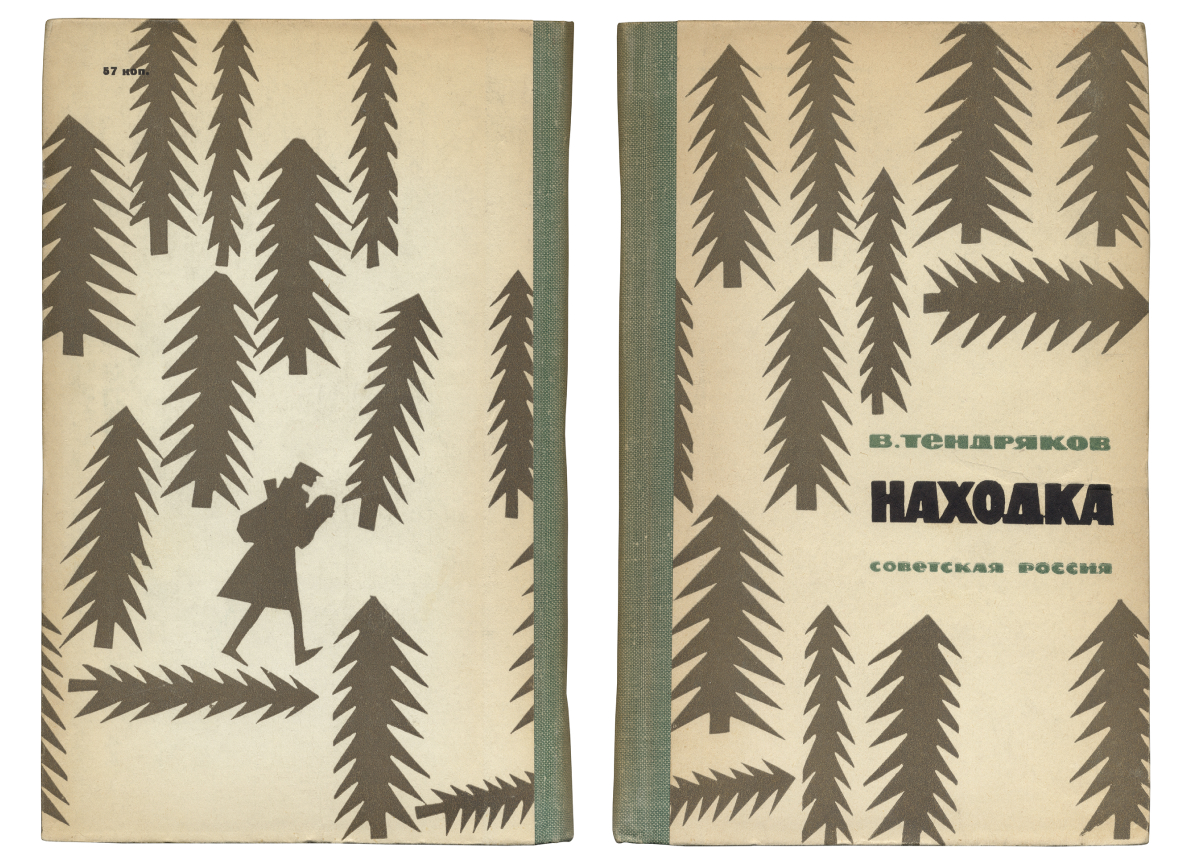
Типографика с лирической поправкой на время
Ху­дож­ник Вла­ди­мир Мед­ве­дев (1931–1999) по­свя­тил жизнь кни­ге и пе­чат­ной гра­фи­ке. Па­ра­док­саль­но, но од­но­го из са­мых яр­ких лю­дей в оте­че­ствен­ном гра­фи­че­ском ди­зай­не вто­рой по­ло­ви­ны XX ве­ка прак­ти­че­ски ни­кто не зна­ет: в се­ти о нём нет ин­фор­ма­ции, за ис­клю­че­ни­ем не­сколь­ких строк. Увы, та­ко­ва участь мно­гих про­фес­си­о­на­лов ушед­шей эпо­хи — скром­ных, чут­ких гра­фи­ков, не­из­вест­ных и по­ны­не.
Прак­ти­че­ски каж­дая пуб­ли­ка­ция о книж­ном ди­зай­не в СССР по­сле­во­ен­но­го вре­ме­ни со­про­во­жда­ет­ся пе­ре­чис­ле­ни­ем имён ху­дож­ни­ков Л. Збар­ско­го, Б. Мар­ке­ви­ча, Ю. Со­осте­ра, од­на­ко за бор­том ча­сто оста­ют­ся ра­бо­ты та­ких ма­сте­ров, как До­бри­цын, Або­ев, Гри­шин, Гро­ман, Эль­ко­нин, Аки­мов, Крей­цер, По­жар­ский, Кляч­ко, Мед­ве­дев (спи­сок мож­но про­дол­жать дол­го). Хо­чет­ся, что­бы по­яв­ля­лось боль­ше со­дер­жа­тель­ных пуб­ли­ка­ций, осно­ван­ных на соб­ствен­ных ис­сле­до­ва­ни­ях, а не на пе­ре­ска­зе уже су­ще­ству­ю­ще­го. Ма­те­ри­а­ла для изу­че­ния мно­го.
Ху­дож­ник Вла­ди­мир Мед­ве­дев в окру­же­нии дру­зей. 1950-е.
Не так дав­но вы­шла кни­га Вла­ди­ми­ра Кри­чев­ско­го «Гра­фи­че­ские зна­ки От­те­пе­ли», по­свящён­ная уни­каль­ной книж­ной гра­фи­ке 1960-х. На стра­ни­цах кни­ги про О-стиль (ав­тор­ский нео­ло­гизм) сре­ди со­тен ра­бот мож­но най­ти из­да­ния, оформ­лен­ные Вла­ди­ми­ром Мед­ве­де­вым. Они вы­де­ля­ют­ся не­обыч­ной ком­по­зи­ци­ей, иг­рой шриф­то­вых форм, кон­трас­том кеглей, но при этом оста­ют­ся сдер­жан­ны­ми и ак­ку­рат­ны­ми. Гра­фи­че­ский об­раз От­те­пе­ли во мно­гом сфор­ми­ро­вал­ся бла­го­да­ря Мед­ве­де­ву, ведь боль­шая часть мо­сков­ских книж­ных ше­дев­ров 60-х по­яви­лась в «Со­вет­ском пи­са­те­ле», где он тру­дил­ся глав­ным ху­дож­ни­ком и ху­до­же­ствен­ным ре­дак­то­ром.
Вла­ди­мир Кри­чев­ский. Гра­фи­че­ские зна­ки От­те­пе­ли. М.: Арт-Вол­хон­ка, 2018.
В ис­то­рии оте­че­ствен­ной гра­фи­ки эпо­ха От­те­пе­ли (с боль­шой бук­вы!) сы­гра­ла важ­ную роль: в книж­ный ди­зайн вер­ну­лась ис­крен­ность, дав­шая осо­бый им­пульс шриф­то­вой гра­фи­ке, но­во­му язы­ку об­ра­зов. Абрис сдво­ен­ных лиц, че­ло­ве­че­ская фи­гу­ра, де­вуш­ка, цве­ты и, ко­неч­но, солн­це — вот лишь не­боль­шой спи­сок объ­ек­тов, сим­во­ли­зи­ру­ю­щих рас­цвет и вес­ну в от­те­пель­ной кни­ге. И ещё один не­ма­ло­важ­ный мо­мент: со­вет­ская кни­га не стре­ми­лась за­мкнуть­ся, от­го­ро­дить­ся от внеш­не­го ми­ра и меж­ду­на­род­но­го куль­тур­но­го кон­тек­ста. В из­да­тель­ствах «Выс­шая шко­ла» и «Про­гресс» вы­хо­ди­ли кни­ги на ино­стран­ных язы­ках, ко­то­рые и се­го­дня встре­ча­ют­ся в ев­ро­пей­ских бу­ки­ни­сти­че­ских лав­ках, на книж­ных раз­ва­лах и он­лайн-аук­ци­о­нах. Обиль­но ил­лю­стри­ро­ван­ная кни­га как жанр ста­ла яр­ким сви­де­тель­ством очень ко­рот­кой и пло­до­твор­ной эпо­хи. К со­жа­ле­нию, вме­сте с фе­но­ме­ном От­те­пе­ли по­га­сла и куль­ту­ра гра­фи­ки, о чём свидетельствуют сло­ва са­мо­го Вла­ди­ми­ра Мед­ве­де­ва по­сле по­се­ще­ния X Мо­сков­ской книж­ной яр­мар­ки в 1997 го­ду:
«Яр­мар­ка по­ка­зы­ва­ет, что ис­чез­ла куль­ту­ра книж­но­го оформ­ле­ния, бо­лее то­го, уби­то це­лое по­ко­ле­ние книж­ных ху­дож­ни­ков, ко­то­рые со­став­ля­ли гор­дость ев­ро­пей­ской гра­фи­ки. Эти лю­ди ушли не­по­нят­но во что и за­ни­ма­ют­ся чем угод­но, толь­ко не книж­ным оформ­ле­ни­ем. По­смот­ри­те на стен­ды, что ри­су­ют и как оформ­ля­ют. Ужас. Пол­ная де­гра­да­ция».
Не слу­чай­но Вла­ди­мир Ва­си­лье­вич упо­ми­на­ет о ри­со­ва­нии. Руч­ная ра­бо­та яв­ля­ет­ся осно­вой для при­да­ния фор­мы аб­со­лют­но лю­бо­му объ­ек­ту. Ис­то­ри­че­ски сло­жи­лось, что оте­че­ствен­ная гра­фи­че­ская куль­ту­ра, в том чис­ле и шриф­то­вая, бы­ла имен­но ри­со­валь­ной. Ху­дож­ник мог не вла­деть шриф­том, че­го не ска­жешь о ри­сун­ке, и не слу­чай­но по­чти весь XX век вну­три кни­ги та­кое вни­ма­ние уде­ля­ли ил­лю­стра­ции. В 60-е го­ды слу­чил­ся как ил­лю­стра­тив­ный, так и шриф­то­вой бум, в осно­ве ко­то­ро­го бы­л ри­су­нок. Мед­ве­дев пер­во­класс­но вла­дел ри­сун­ком, в част­но­сти пе­рье­вым, ли­ней­ным. Но и ли­ни­ей он не огра­ни­чи­вал­ся, а ис­поль­зо­вал вто­рую тех­ни­ку — острым но­жом вы­ре­зал из чёр­ной бу­ма­ги пят­на и со­став­лял ми­ни­ма­ли­стич­ную кон­траст­ную ком­по­зи­цию с вклю­че­ни­ем бе­ло­го, как это при­ня­то при ра­бо­те над со­зда­ни­ем, на­при­мер, на­бор­но­го шриф­та.
Обра­тим­ся к ра­бо­там ма­сте­ра. Воз­мож­но, са­мая гу­сто­за­селён­ная ёл­ка­ми кни­га за всю ис­то­рию ми­ро­во­го кни­го­пе­ча­та­ния — «На­ход­ка» Вла­ди­ми­ра Тен­дря­ко­ва. По сю­же­ту глав­ный ге­рой про­би­ра­ет­ся че­рез во­сем­на­дцать ки­ло­мет­ров ле­са. В ин­тер­пре­та­ции ху­дож­ни­ка — пол­но­стью ело­во­го. Шрифт в кни­ге (ра­зу­ме­ет­ся, кро­ме основ­но­го на­бор­но­го) ри­со­ван­ный. За­острён­ный лес­ной мас­сив ино­гда встре­ча­ет­ся и в дру­гих кни­гах с ил­лю­стра­ци­я­ми Мед­ве­де­ва.
«У ме­ня нет боль­шо­го опы­та ра­бо­ты в ил­лю­стра­ции. Про­цесс её ро­жде­ния для ме­ня му­чи­те­лен от на­ча­ла до кон­ца. Чрез­вы­чай­но ва­жен и до­лог сбор не­об­хо­ди­мо­го ма­те­ри­а­ла, свя­зан­но­го с сю­же­том и ис­то­ри­ей ил­лю­стри­ру­е­мо­го про­из­ве­де­ния. Чем обиль­нее и ин­те­рес­нее ма­те­ри­ал, тем глуб­же я по­гру­жа­юсь в не­го. Ра­бо­та пе­ре­рас­та­ет все доз­во­лен­ные вре­ме­нем гра­ни­цы, что ча­сто ска­зы­ва­ет­ся на ка­че­стве эс­ки­зов и ори­ги­на­лов».
Так Мед­ве­дев опи­сы­ва­ет про­цесс ра­бо­ты в сборнике о рус­ской книж­ной ил­лю­стра­ции, ку­да по­ме­ще­на од­на из не­мно­го­чис­лен­ных ста­тей ди­зай­не­ра. В ста­тье он от­ме­ча­ет, что ил­лю­стра­ция для не­го — и спо­соб са­мо­вы­ра­же­ния, и воз­мож­ность об­раз­но от­ра­зить вре­мя, а так­же од­но из са­мых ин­те­рес­ных про­яв­ле­ний куль­ту­ры.
«Стре­ла над оке­а­ном» — од­на из ран­них ра­бот. Здесь и от­те­пель­ный ри­со­ван­ный шрифт, и мно­го­об­ра­зие форм, и це­лых шесть раз­ных кра­сок. Кни­га при­ме­ча­тель­на оби­ли­ем ма­лень­ких кар­ти­но­чек-за­ста­вок, не­ти­пич­ных для Мед­ве­де­ва — обыч­но ил­лю­стра­ции у ху­дож­ни­ка круп­ные (на по­ло­су или в пол­по­ло­сы), и встре­ча­ют­ся они не так ча­сто. Тот са­мый са­ноч­ник с ги­гант­ской пти­цей, взя­тый в ка­че­стве «бук­ви­цы» для ста­тьи, по­за­им­ство­ван из этой кни­ги.
Не­льзя не от­ме­тить осве­дом­лён­ность ди­зай­не­ра о (по­ли)гра­фи­че­ских приёмах. Он знал об осо­бен­но­стях книж­но­го ди­зай­на 1930-х, на­при­мер о не­рав­ных друг дру­гу по изоб­ра­же­нию фор­за­цах, ри­со­ван­ном ти­туль­ном раз­во­ро­те, о кар­тин­ке над на­зва­ни­ем на ли­це кни­ги; за­им­ство­вал по­пу­ляр­ные приё­мы 1920-х — рас­паш­ную об­лож­ку (ко­гда изоб­ра­же­ние пе­ре­хо­дит с ли­це­вой сто­рон­ки на зад­нюю), знал и об эти­кет­ке, не го­во­ря уже о круп­ных ак­ци­дент­ных бук­вах. Сле­ду­ю­щие два из­да­ния при­над­ле­жат од­но­му пи­са­те­лю — А. Ку­ле­шо­ву, и вы­шли они из-под ру­ки Мед­ве­де­ва с раз­ни­цей в че­ты­ре го­да. В обе­их кни­гах вид­но об­ра­ще­ние к диа­мет­раль­но про­ти­во­по­лож­ным сти­лям — по­чув­ствуй­те раз­ни­цу.